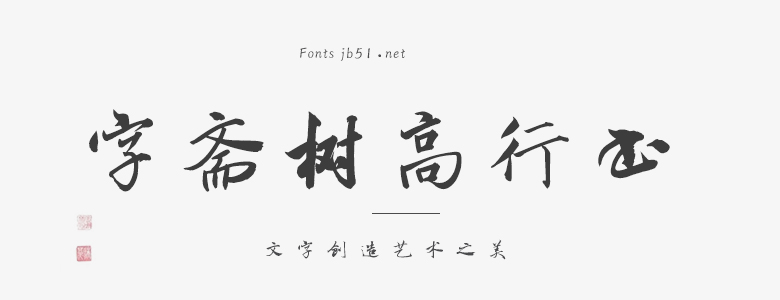
《字齋樹(shù)高行書(shū)》書(shū)寫(xiě)質(zhì)量極高,筆法相當(dāng)靈活又老道,結(jié)構(gòu)講究,書(shū)寫(xiě)流暢規(guī)矩,錯(cuò)落有致,顯得風(fēng)歸致遠(yuǎn),頗具玩味??梢院芎玫膽?yīng)用于文本裝潢、信息展示、網(wǎng)頁(yè)設(shè)計(jì)、篆刻制模、數(shù)據(jù)制作、裝潢設(shè)計(jì)、計(jì)算藝術(shù)設(shè)計(jì)、視覺(jué)設(shè)計(jì)、字帖等一切合法應(yīng)用場(chǎng)景,有喜歡的朋友可免費(fèi)下載收藏。